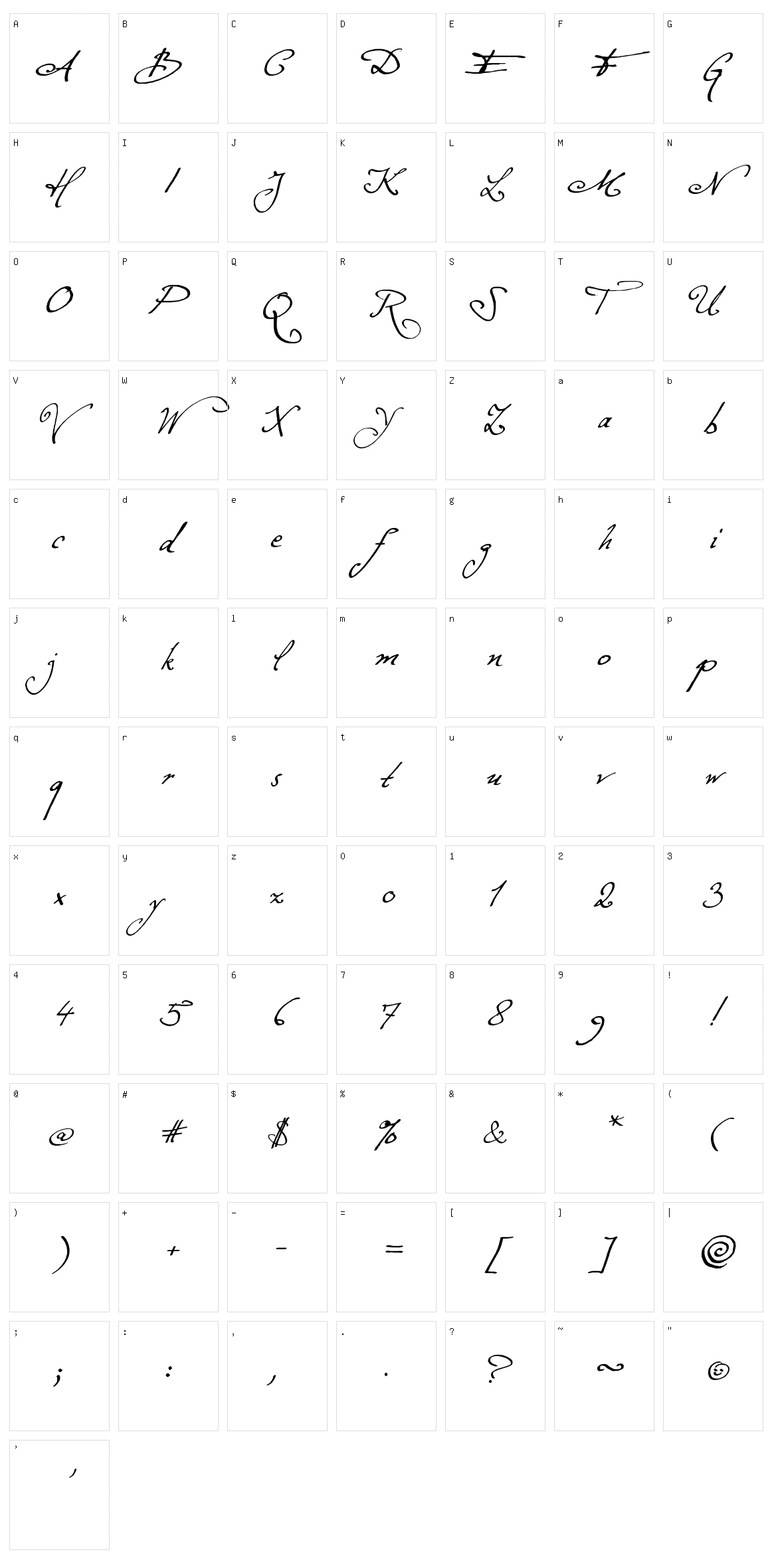
Die beiliegende Schriftart basiert auf der Handschrift von Borys Liechti im Jahre 2000.
Einige Besonderheiten zur Beachtung:
- Optimale Größe: 36 Punkt
- Es sind bewusst keine Gänsefüßchen (x und x), sondern nur französische (= eckige) Anführungszeichen vorhanden. Tastaturcodes: Alt+174 und Alt+175, «x», bzw. »x«.
- Anstelle des unnützen Zollzeichens " (Pest und Verderben über jeden, der dieses Zeichen als Anführungszeichen missbraucht!) ist ein Smiley implementiert.
- Keine Wörter in Majuskeln oder gar Kapitälchen in dieser Schriftart schreiben! Das klappt garantiert nicht...
- Bei Anführungszeichen vor Großbuchstaben muss unter Umständen ein Leerzeichen eingefügt werden, da die Majuskeln häufig nach links «ausschwenken» und sich somit mit dem Anführungszeichen überschneiden können.
- Der Zeilenabstand muss für ein authentisches und ausgewogeneres Schriftbild manuell reduziert werden. Dies konnte ich leider beim Erstellen der Datei nicht festlegen, weil das automatisch (und leider zu groß) berechnet wurde.
- Es ist möglich, die Schrift noch mehr zu neigen, indem man sie einfach kursiv formatiert. Das ist dann aber natürlich nicht mehr authentisch, aber durchaus auch noch ästhetisch...